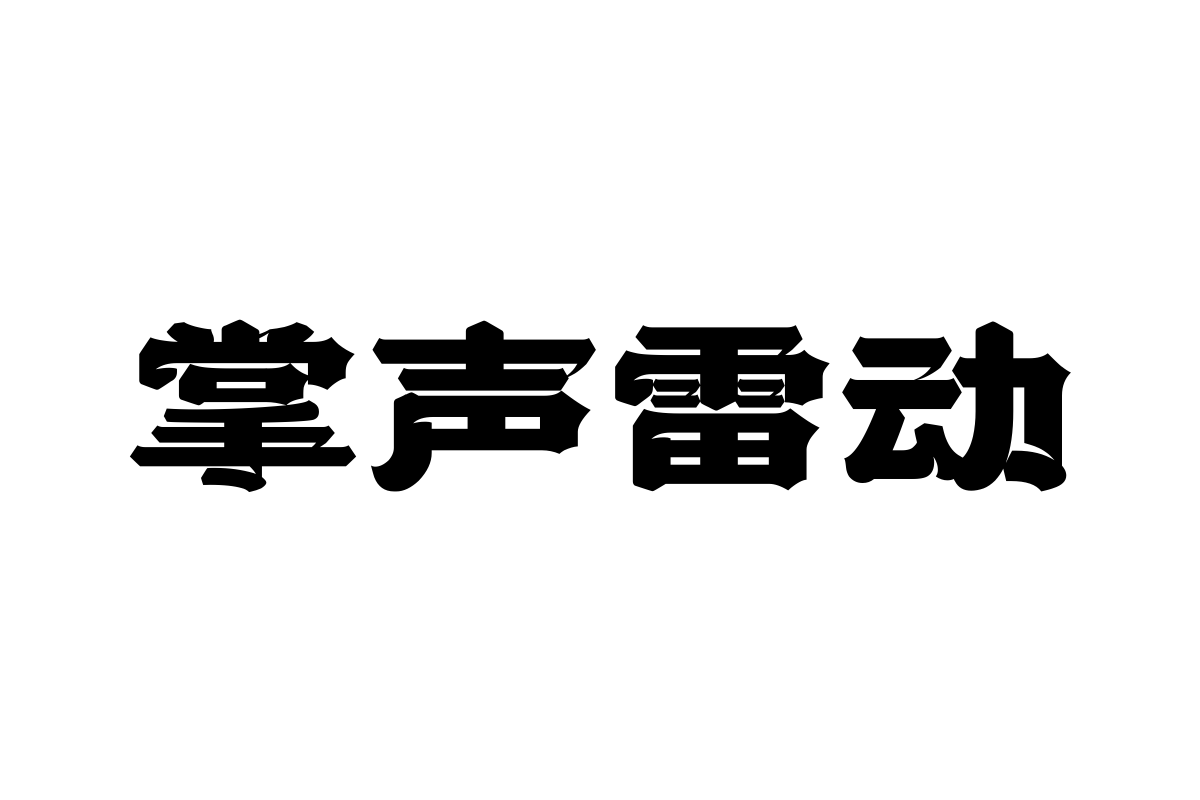
上首混沌体是一款独特的字体,它结合了传统书法的韵味和现代设计的理念。这款字体以其独特的笔画结构和流畅的线条而著称,给人一种既古典又现代的感觉。
上首混沌体的笔画粗细不一,既有粗犷的线条,又有细腻的笔触,使得整个字体看起来既有力量感又不失柔美。它的结构紧凑而富有变化,既有传统的隶书、篆书的韵味,又融入了楷书、行书的元素,使得整体风格独特而新颖。
此外,上首混沌体还注重字与字之间的间距和空间感,使得整个字体看起来更加和谐而富有层次感。它的字形大小适中,既不过于夸张也不过于拘谨,适合用于各种场合的书写和设计。
总的来说,上首混沌体是一款集传统与现代于一体的字体,它的独特之处在于其独特的笔画结构和流畅的线条,使得整个字体既有古典的韵味又不失现代的设计感。无论是用于书法创作还是设计领域,上首混沌体都是一款值得尝试的优秀字体。